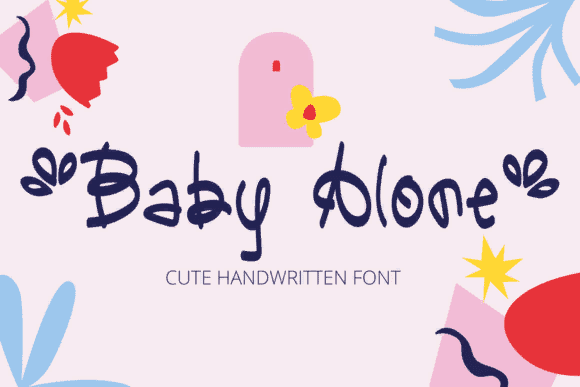
Название: Baby AloneFont (2021)
Baby Alone - это милый и причудливый рукописный шрифт.
Он воплощает игривость и подлинность и идеально подходит для любого детского мероприятия или школьного проекта.